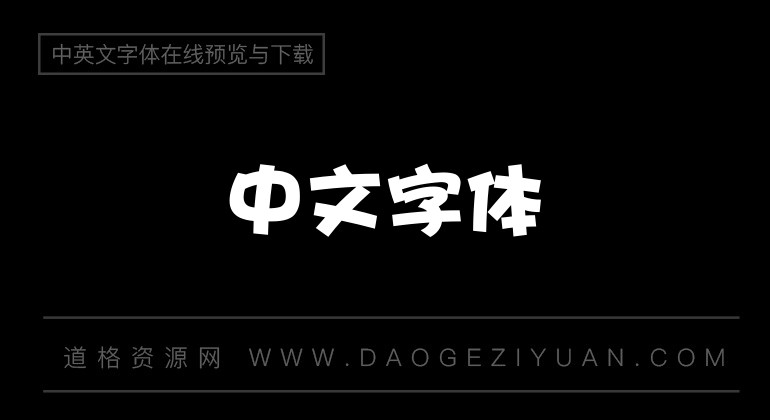
开心软件魔法简体
开心软件魔法简体字体是一款由开心软件开发的汉字字体,具有灵动、活泼、清新、可爱的特点。它采用折叠线条设计,拥有清新脱俗的笔画,使用起来更加轻松,更加悦目。它的笔画有着清晰的轮廓,使用者可以更加清楚的感受到字体的细节,更有利于用户更加深入的了解字体。此外,它还拥有良好的可读性,可以满足各类文档的阅读需求。
开心软件魔法简体是一款非常不错的手写艺术字体,具有很好的视觉感,适合于文化类的宣传设计、商业类品牌的广告和产品包装设计以及个性化文字排版等较多场景。